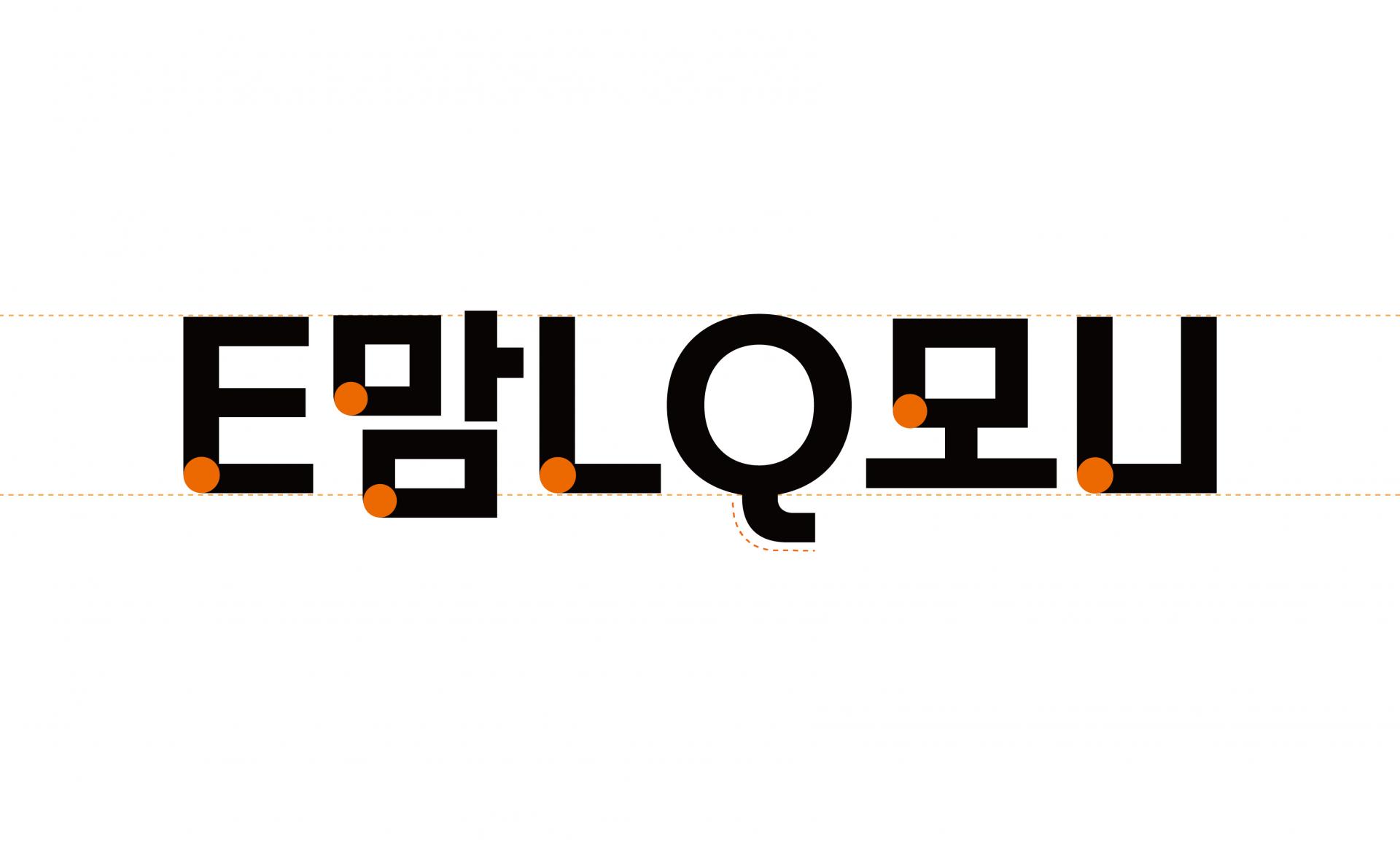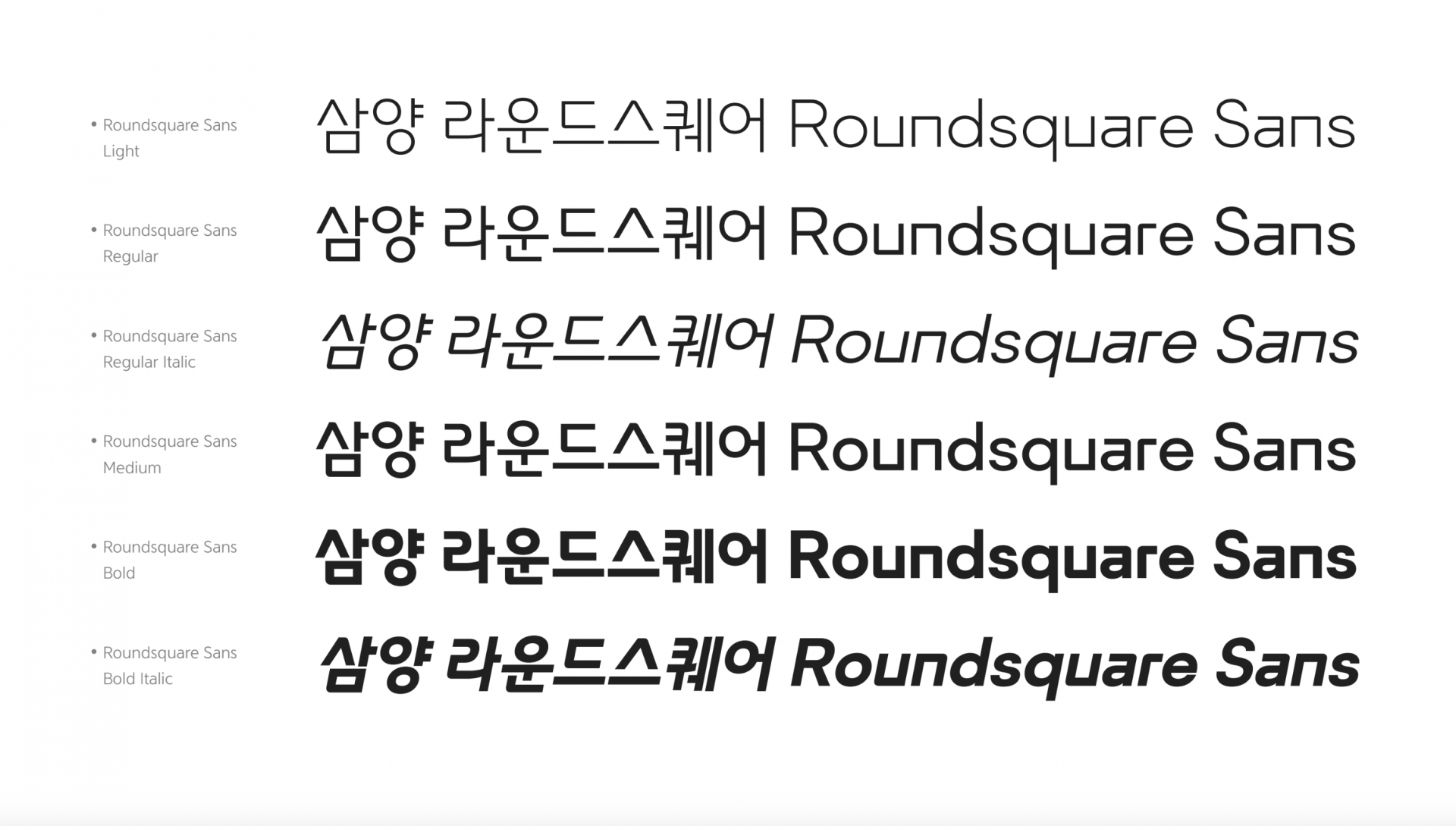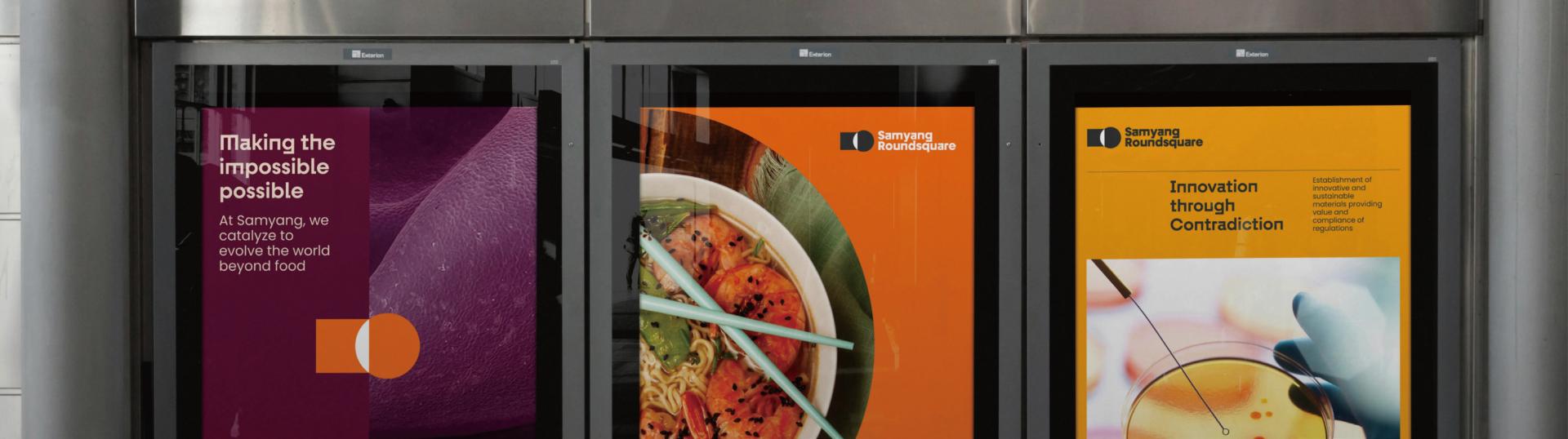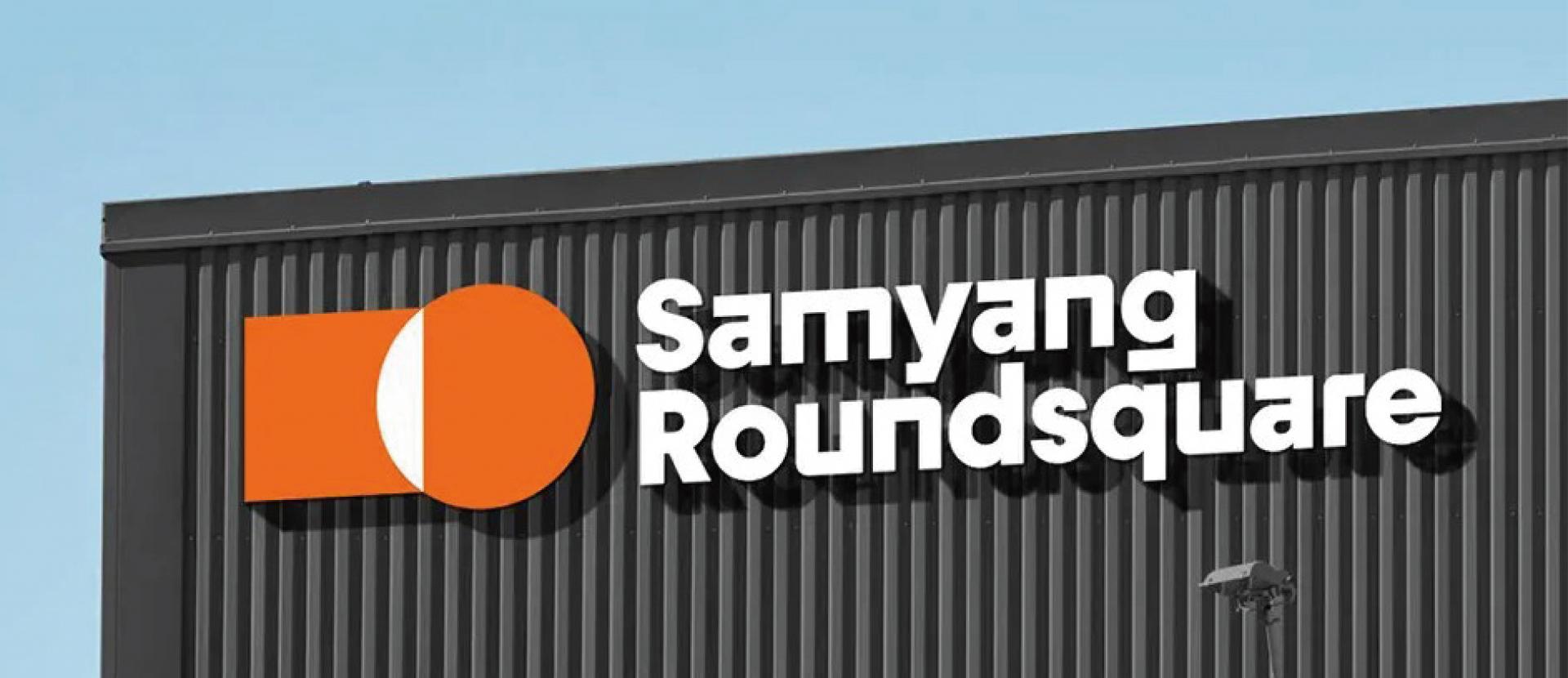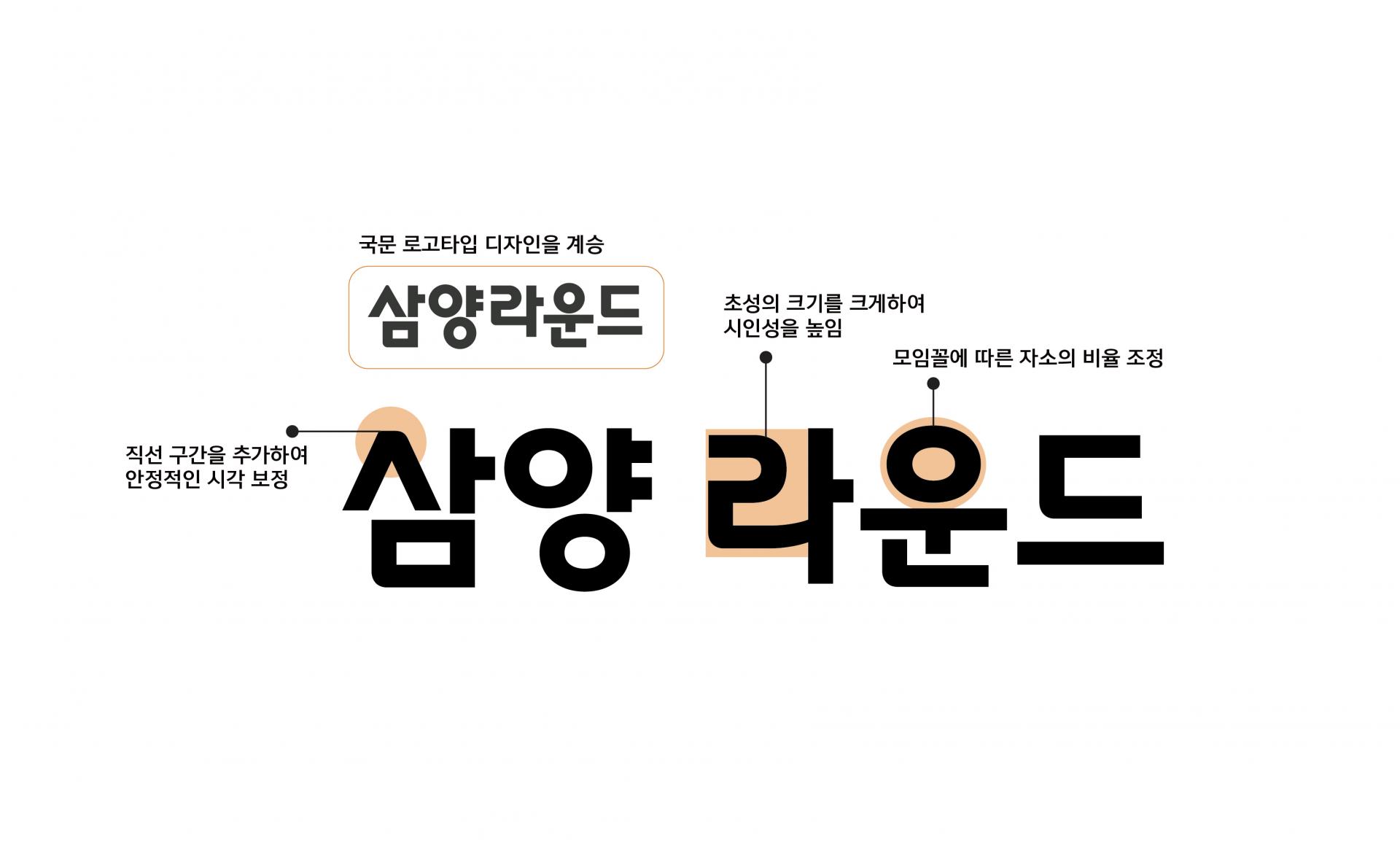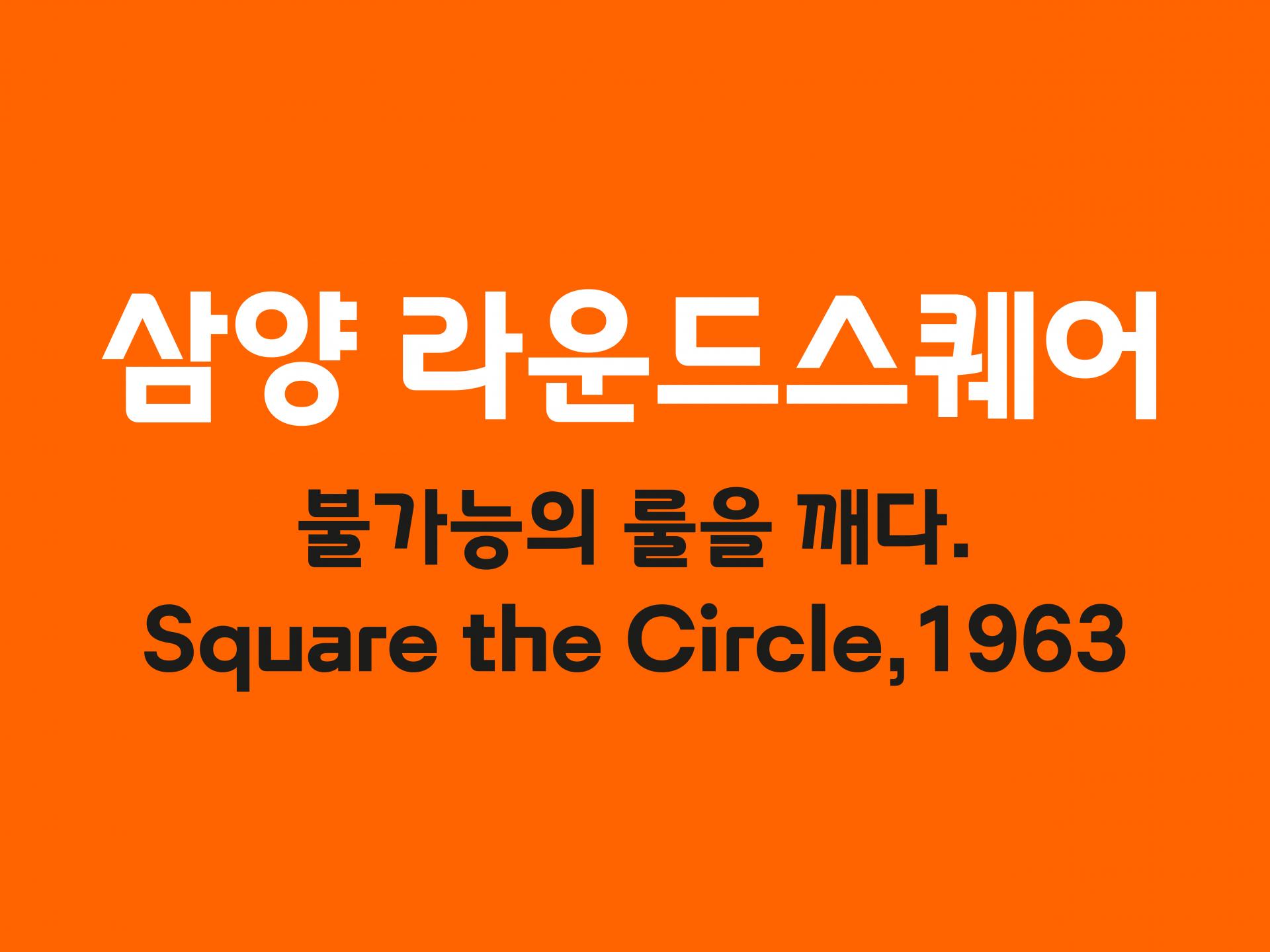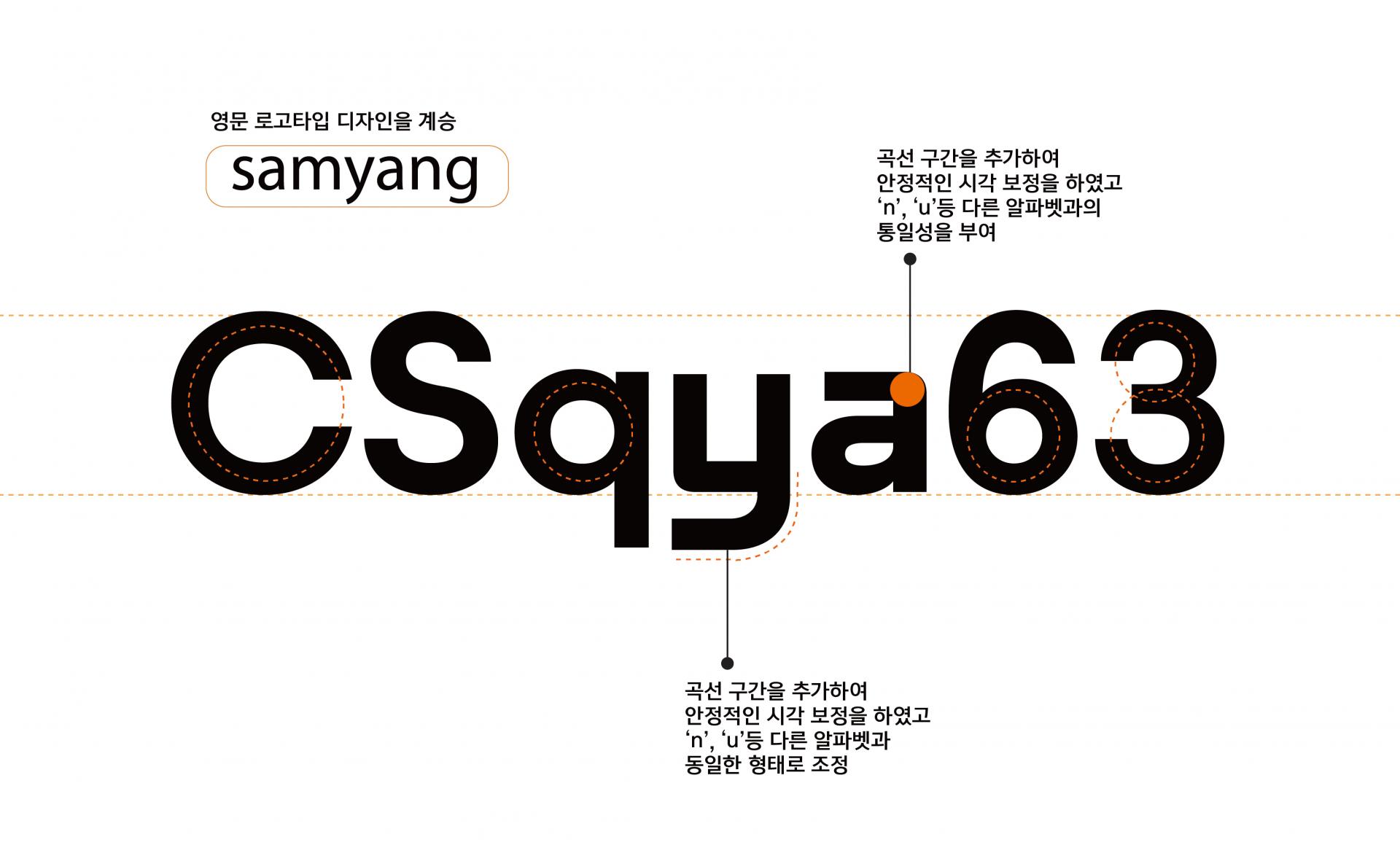
삼양라운드스퀘어 [RoundsquareSans]
삼양 라운드스퀘어의 국문 및 영문 로고 타입 디자인을 계승하여, 라운드와 스퀘어에서 보여지는 기하학적인 인상을 담았다.
6종 / 한글 11,172자(L, R, R Italic, M) 한글 2,350자(B, B Italic / 영문 94자 / KS특수문자 986자